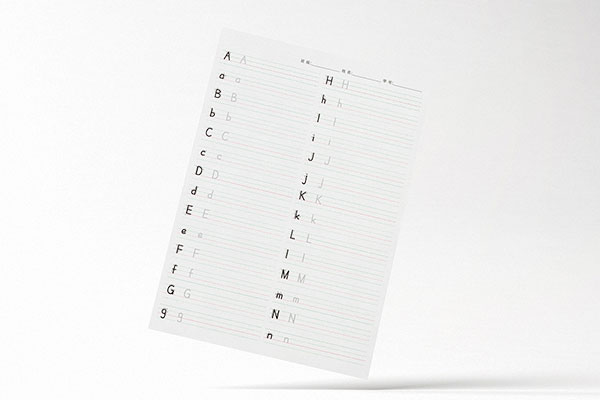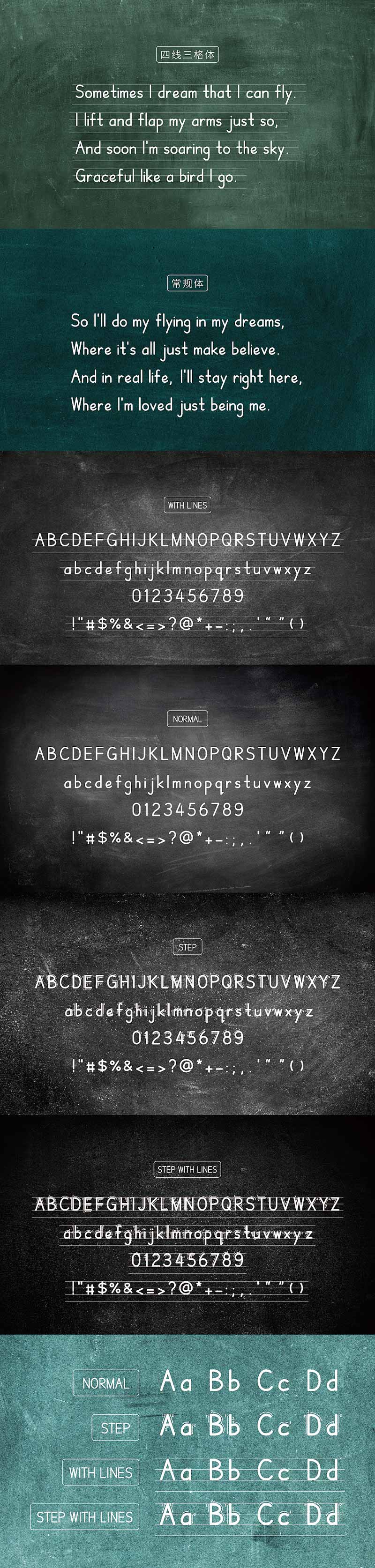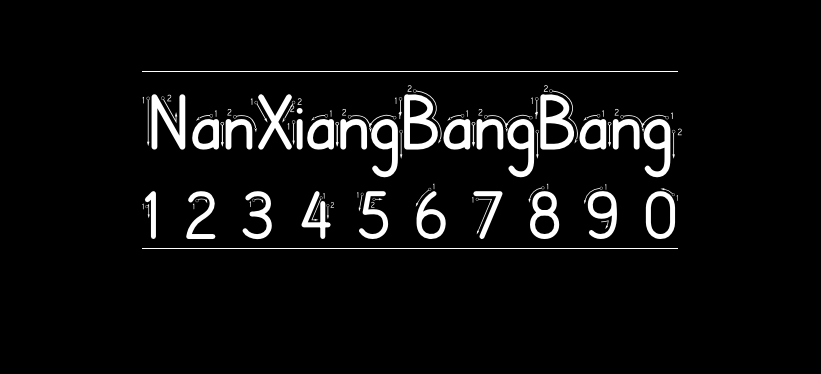
字体下载 南翔棒棒体
南翔棒棒体
南翔棒棒体(Nanxiangbangbang)是一款超有爱的字体,作者为上海的平面设计师南翔小龙,他为了给儿子做个小学英文字帖,找了好久,上海要求学生书写的是一种叫做棒棒体的英文字体,和我们小时候的写法大相径庭,找了一圈也没有发现合适的字体!
索性自己做一套英文字体,包含:常规体、四线三格体、笔序体、笔序四线三格体,福利大众……
南翔棒棒体